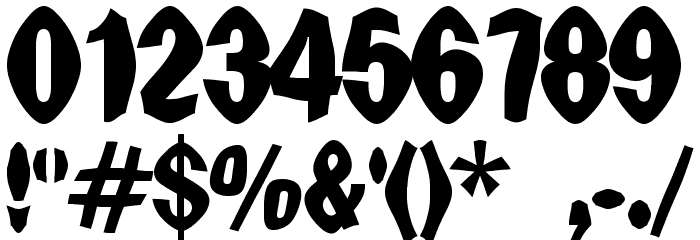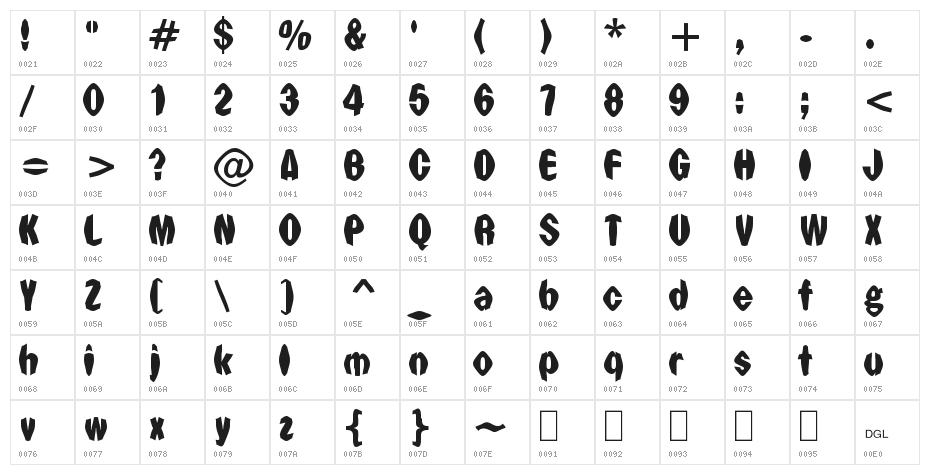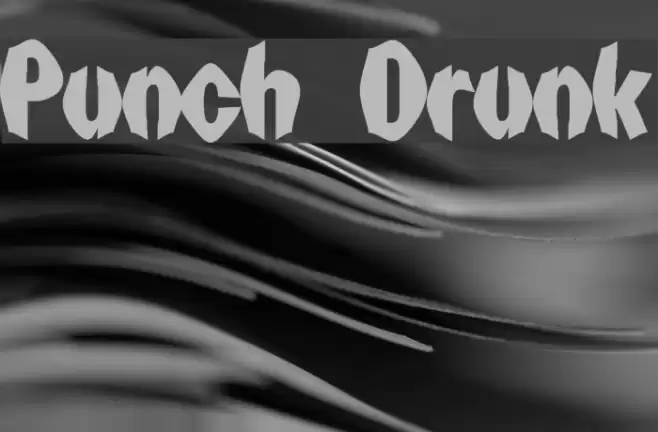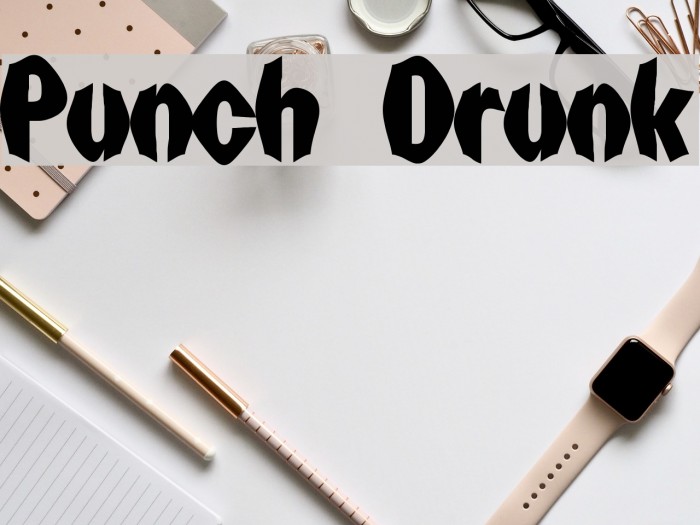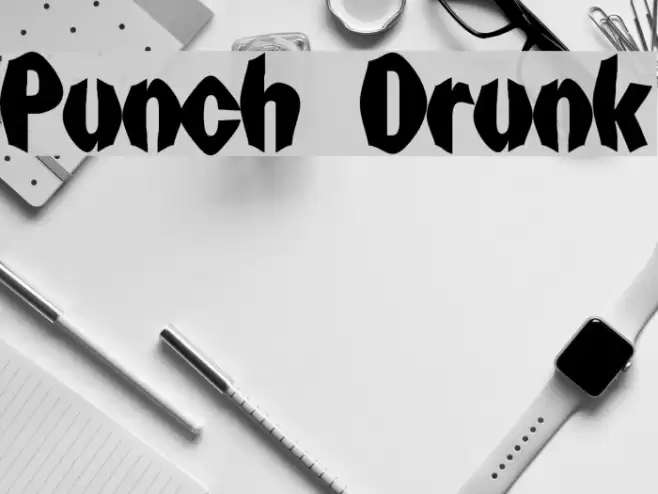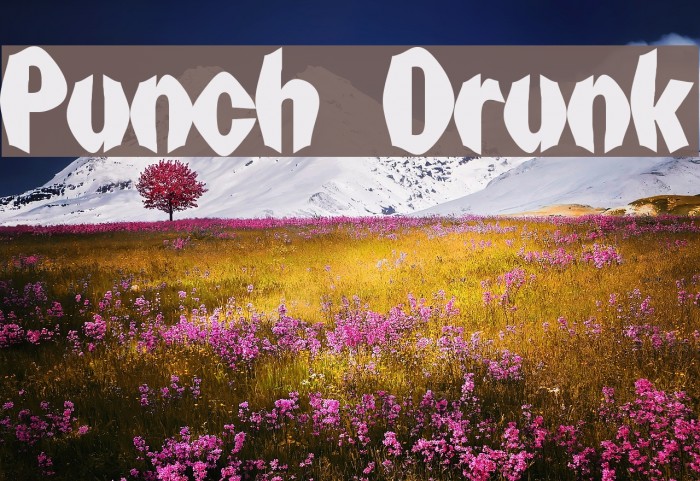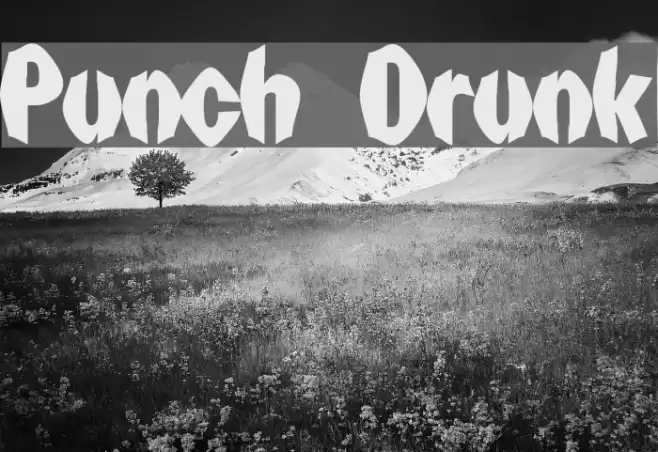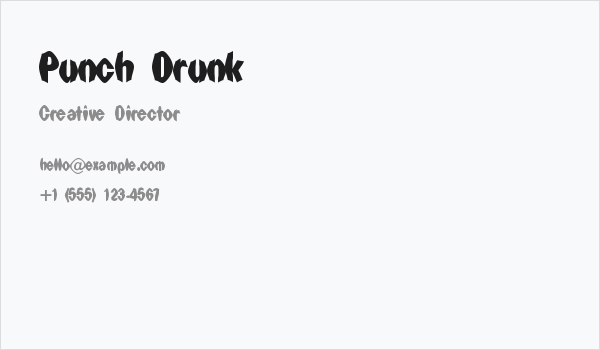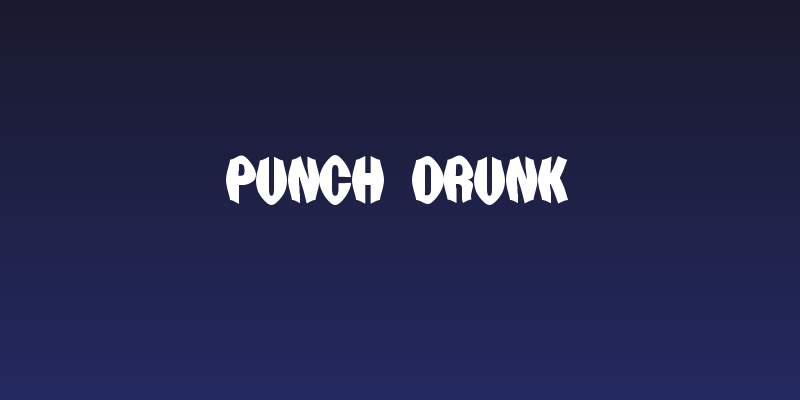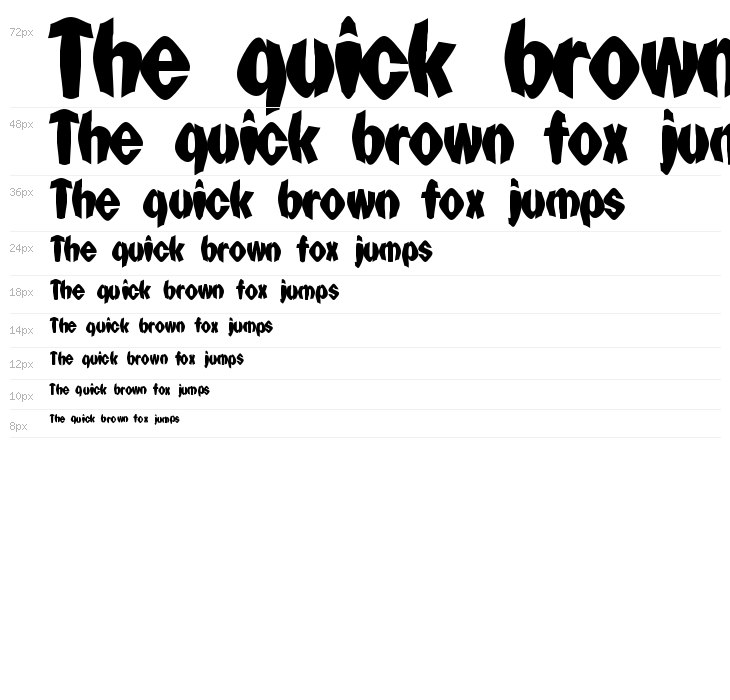
Punch Drunk Font
| Estilo geral | Playful, Whimsical |
| Caso de uso | Headlines, Posters, Creative Branding |
| Projetos propostos | Ideal for posters, children's books, playful branding, and creative advertising. |